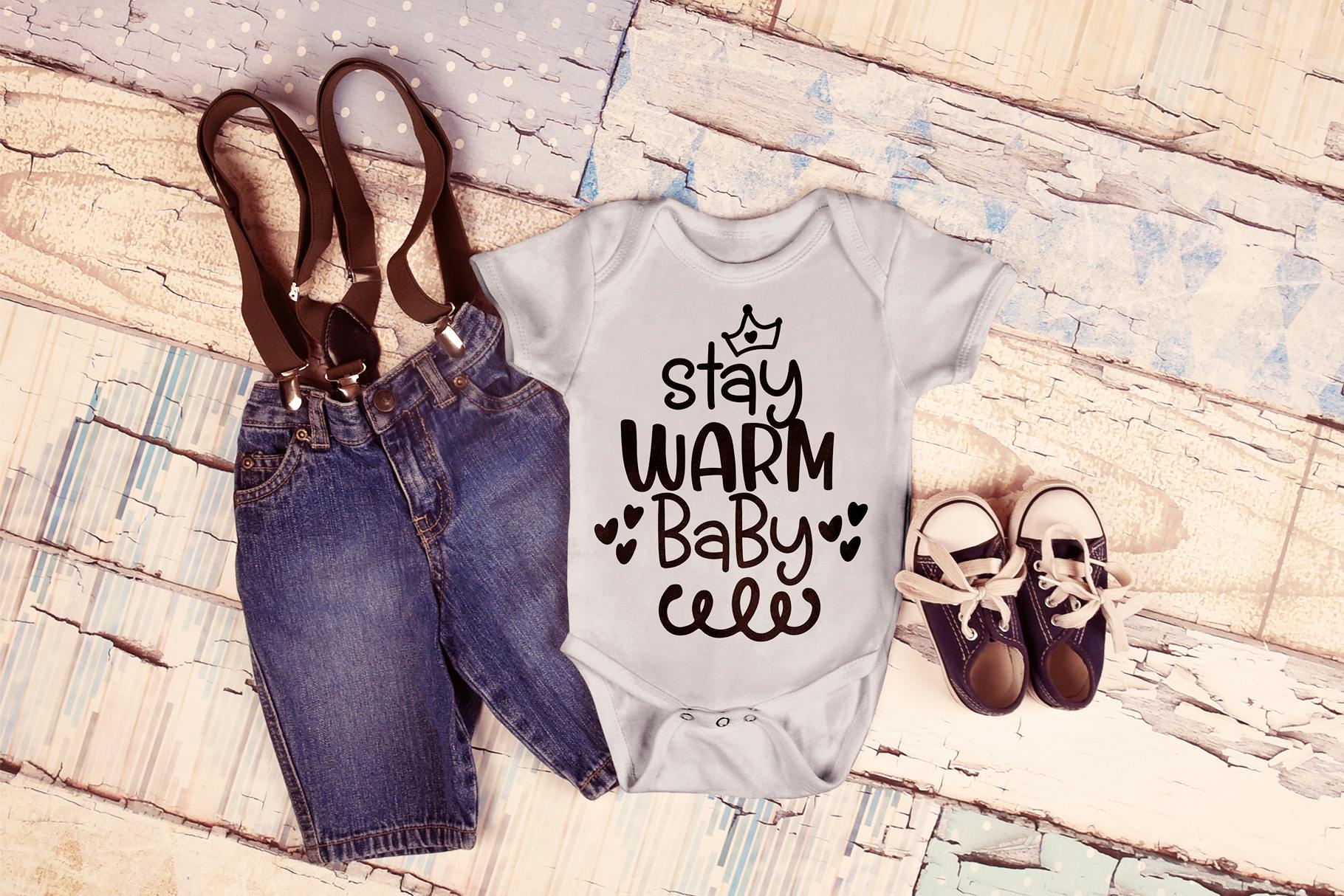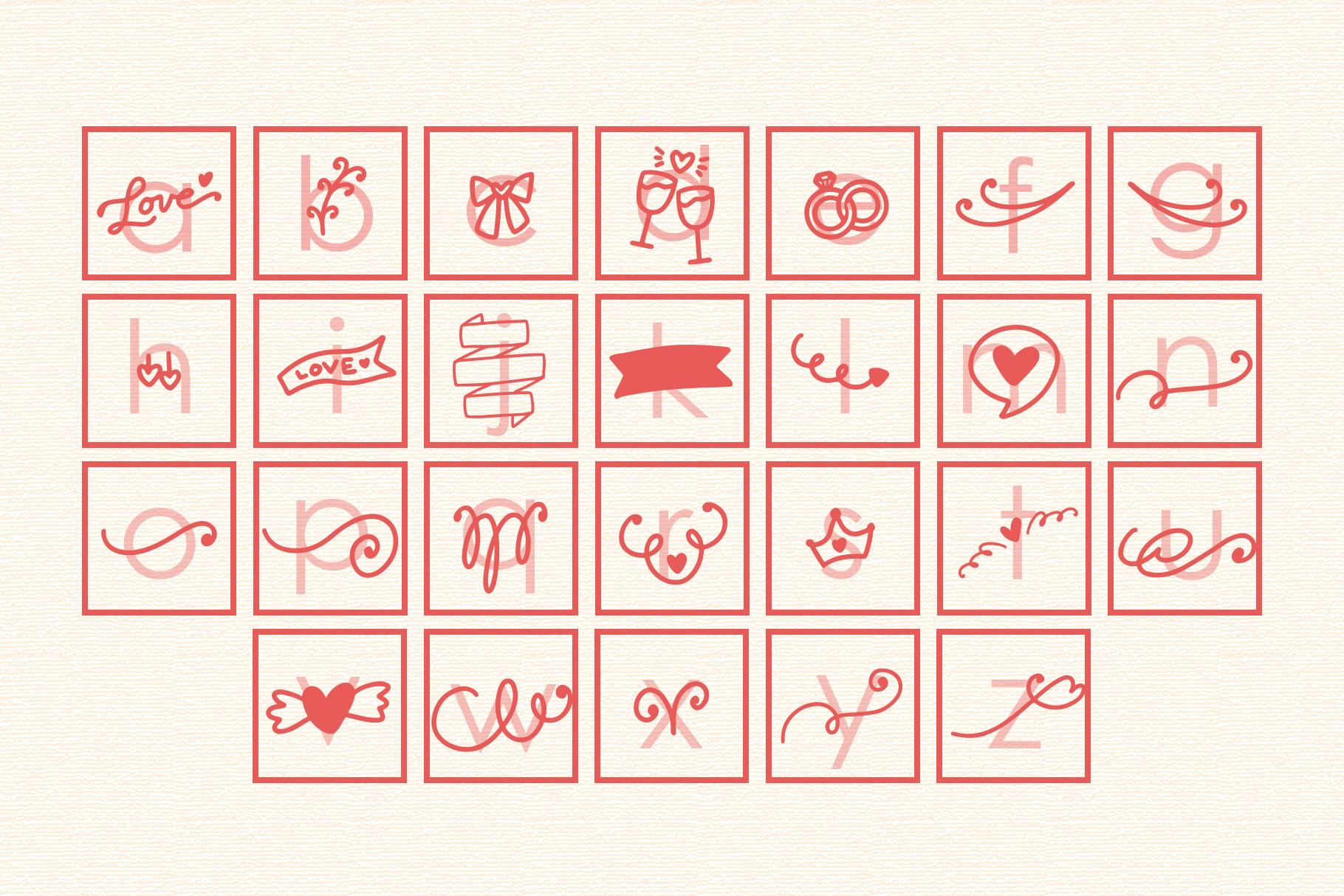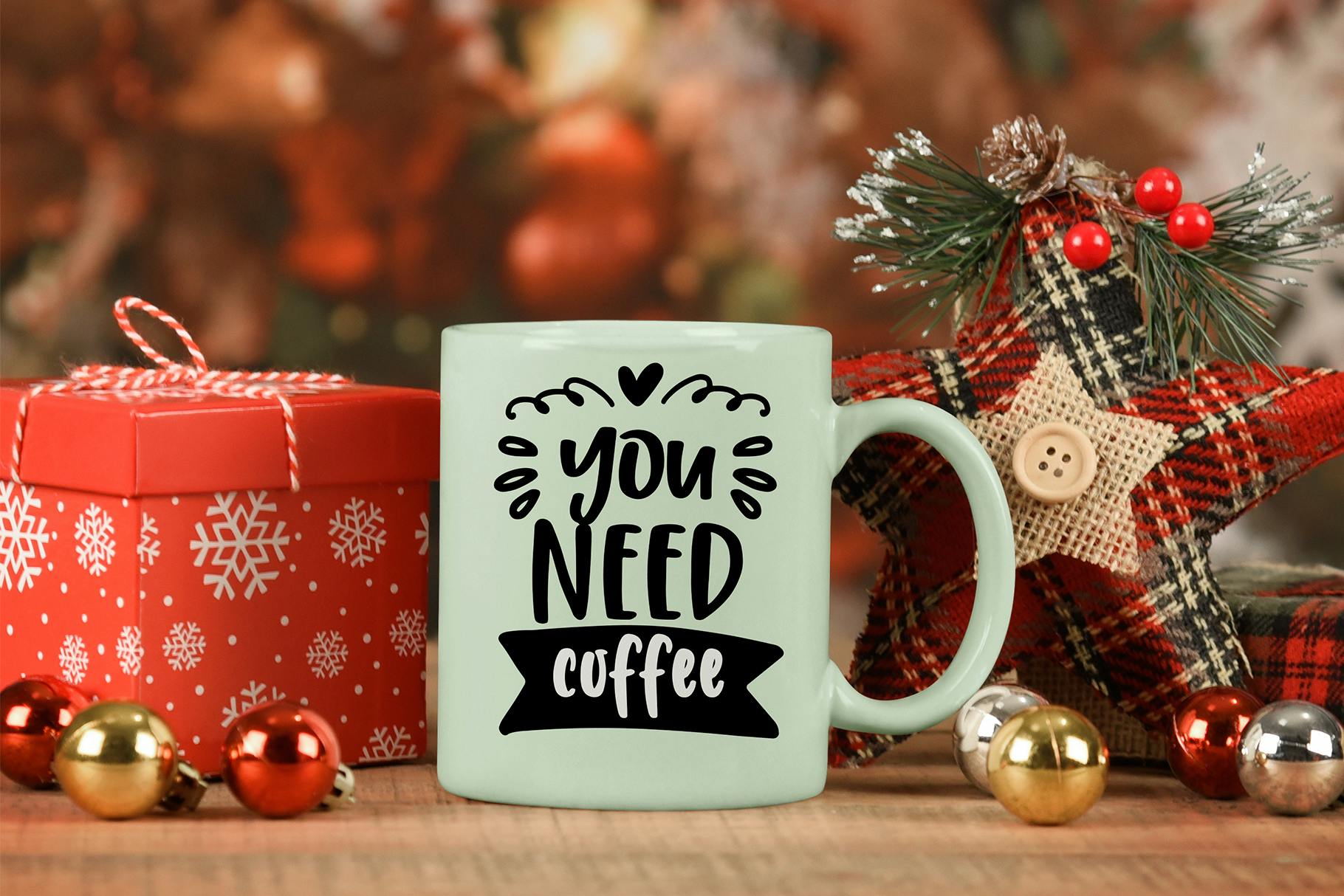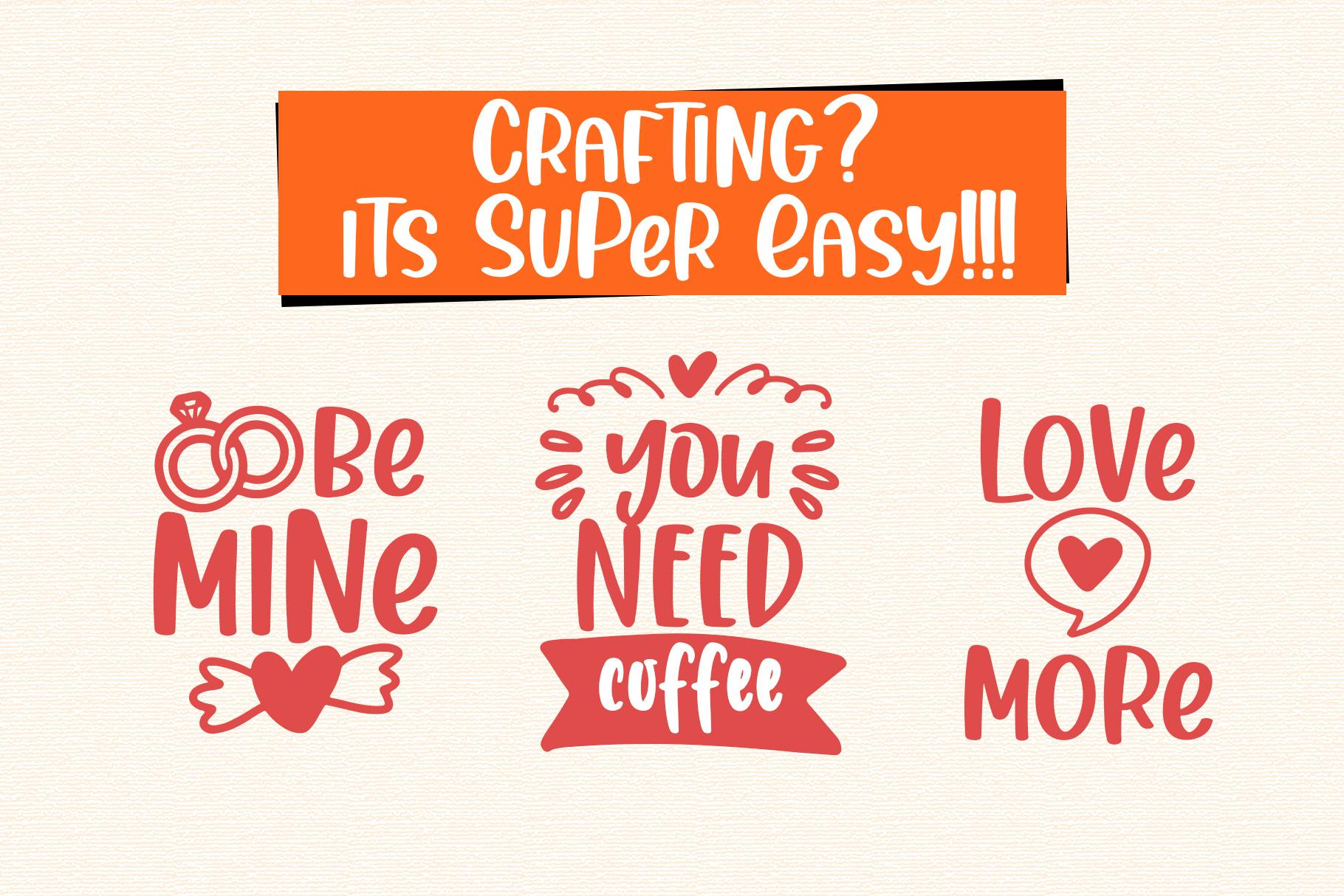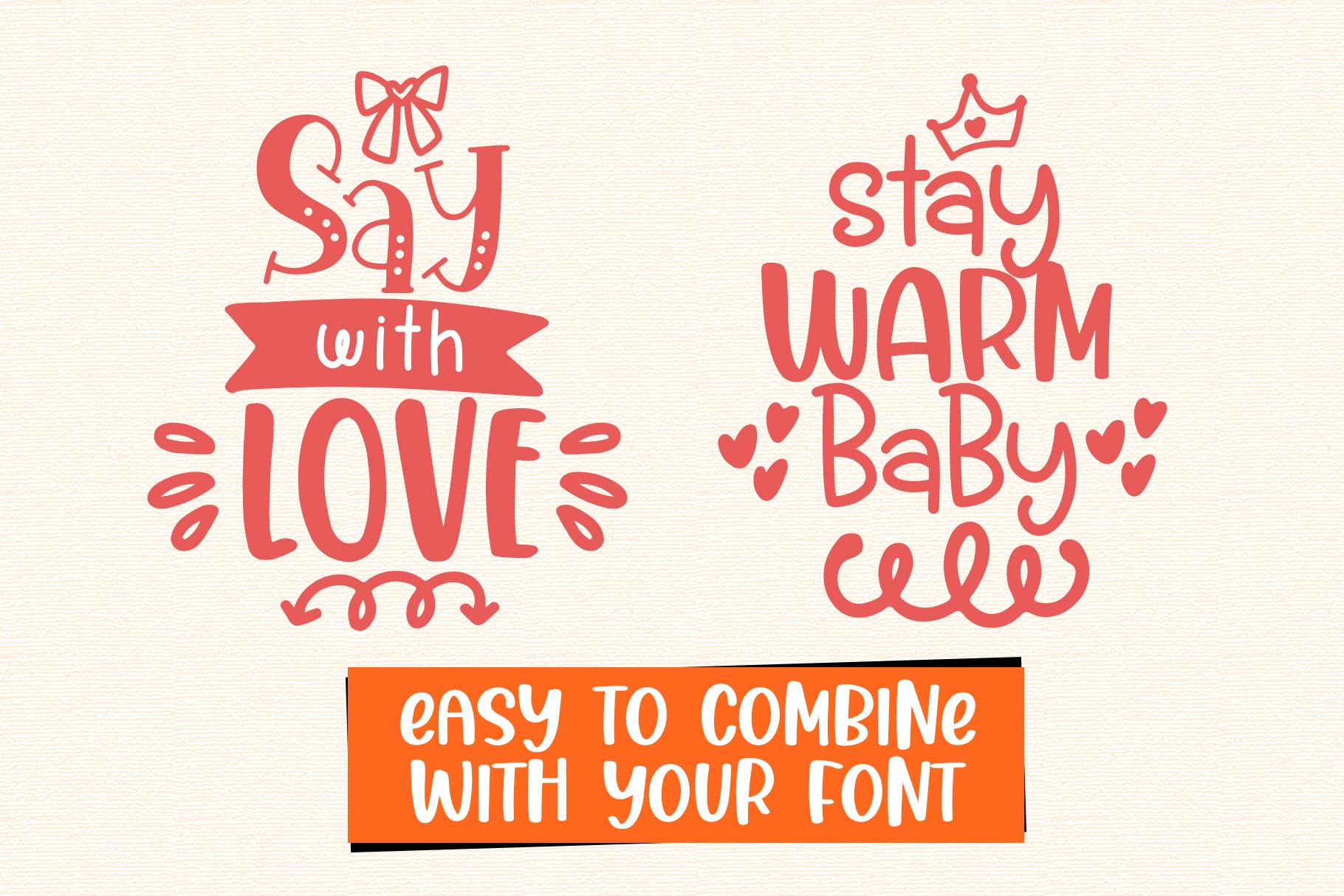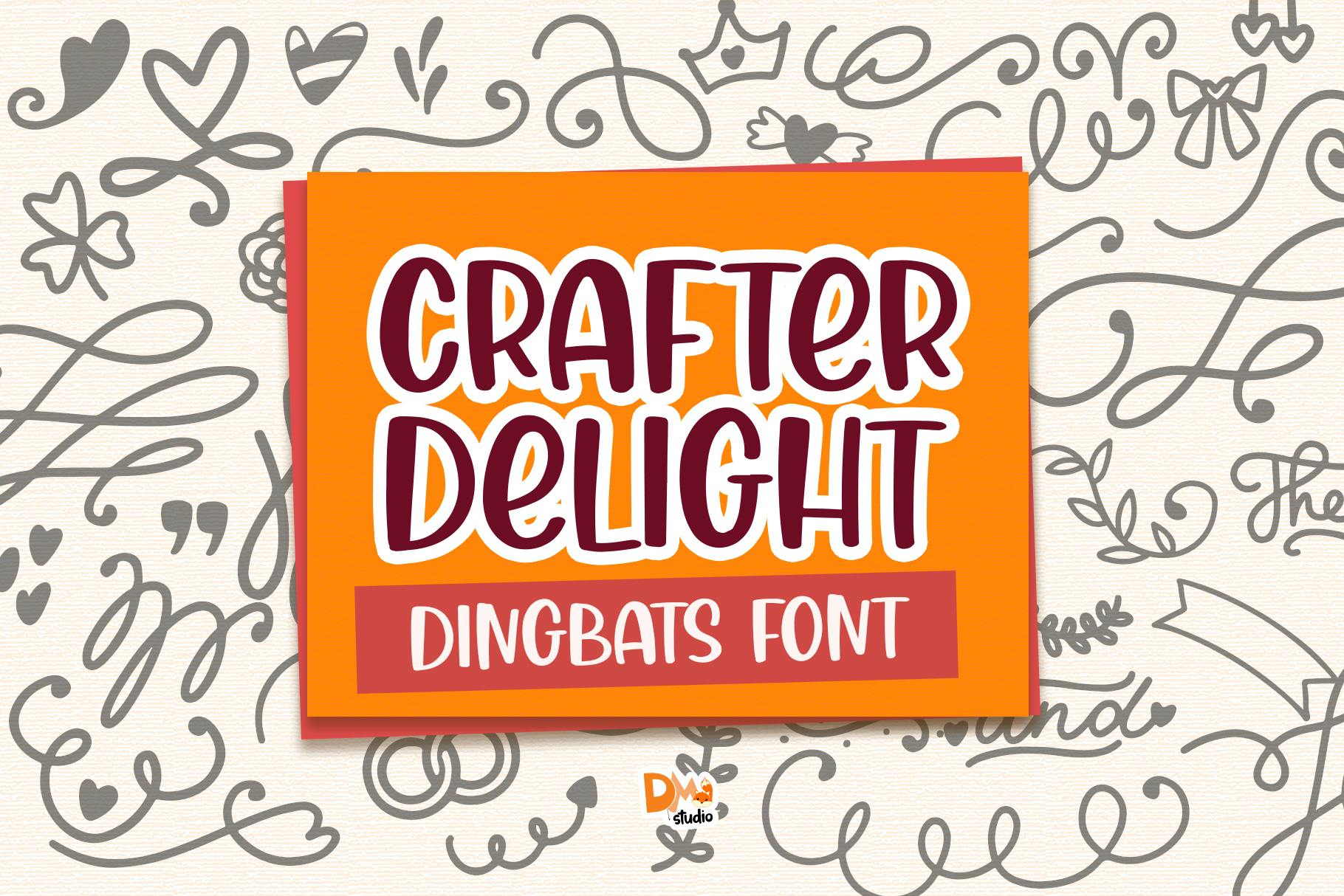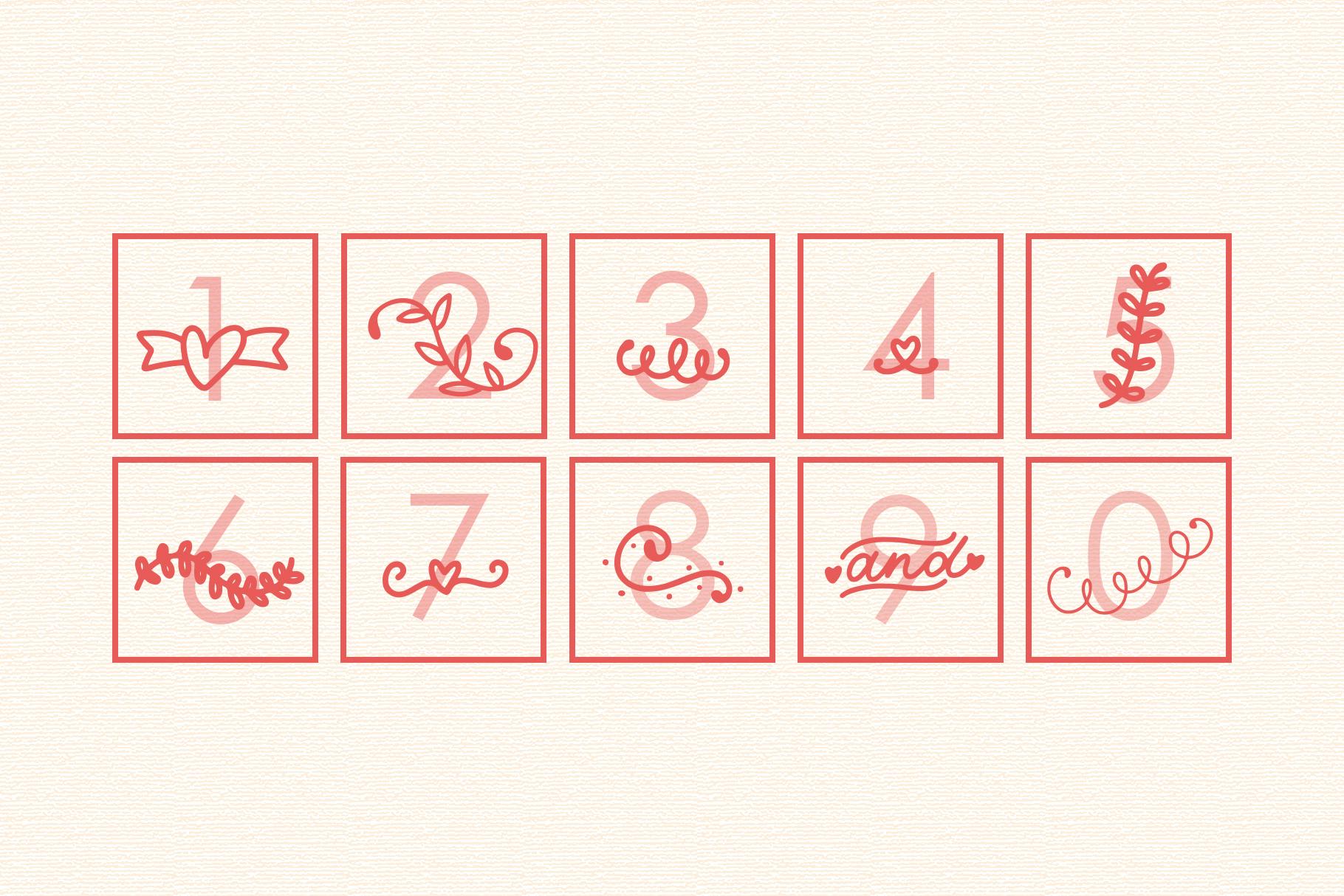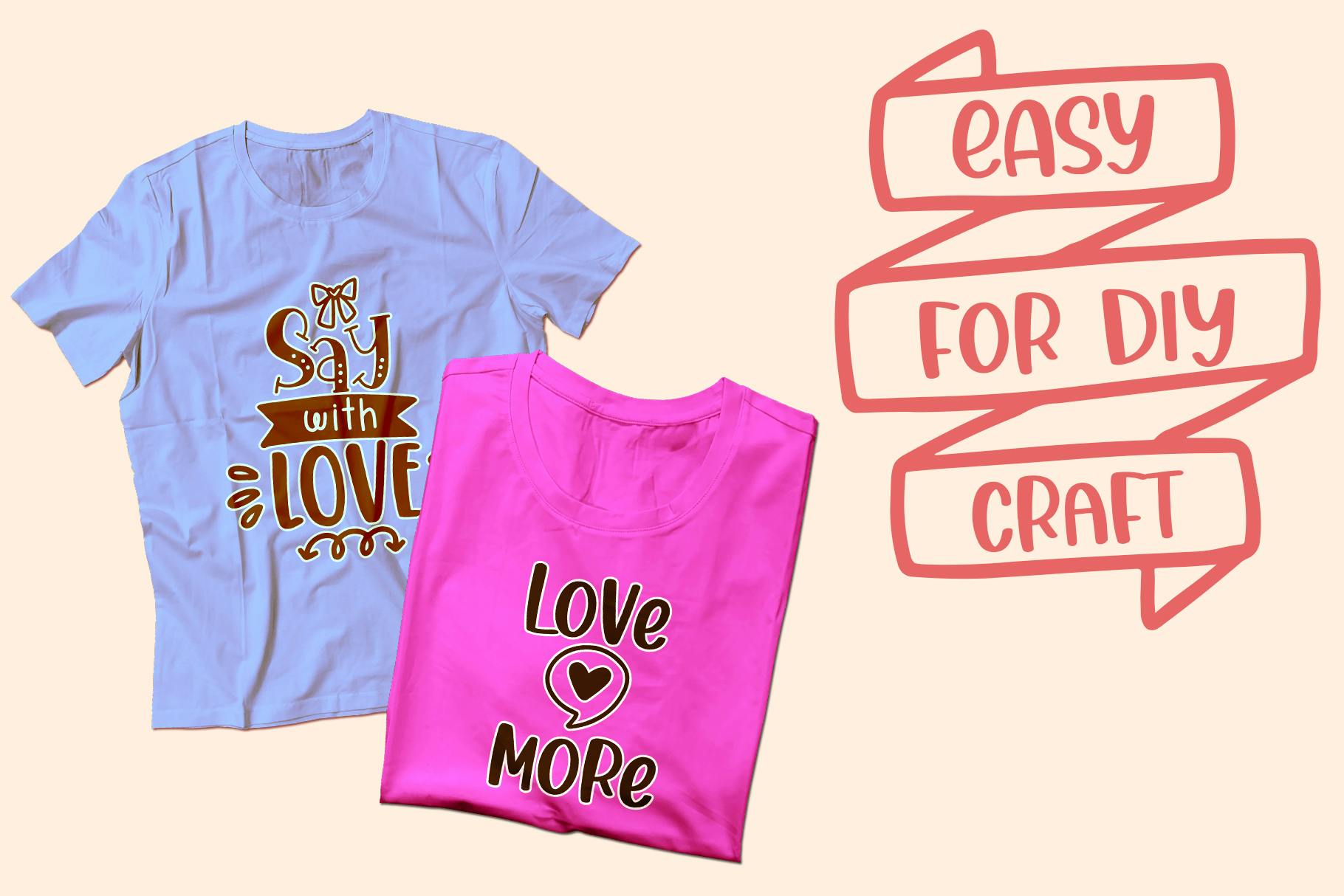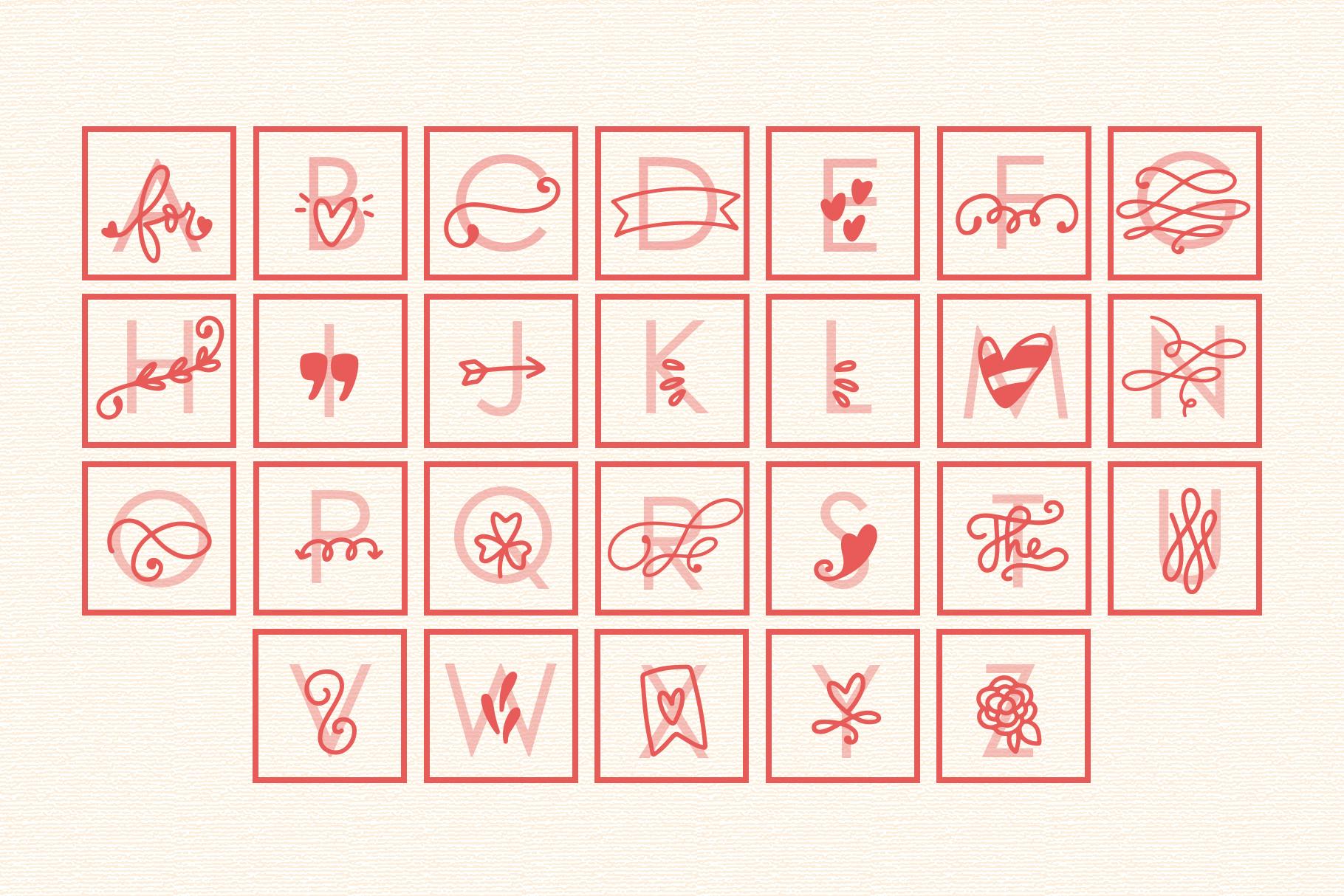
فونت Crafter Delight Dingbats
فونت Crafter Delight Dingbats مجموعهای از 62 دوده زیبا و دوستداشتنی است که در یک فونت جمعآوری شده است. این فونت برای افرادی که به کارهای دستی، پروژههای DIY، چاپ، نقلقولها و طراحی SVG علاقه دارند، طراحی شده است. این فونت کار را برای شما آسانتر میکند؛ فقط کافی است در نرمافزار خود تایپ کنید و از طراحیتان لذت ببرید!